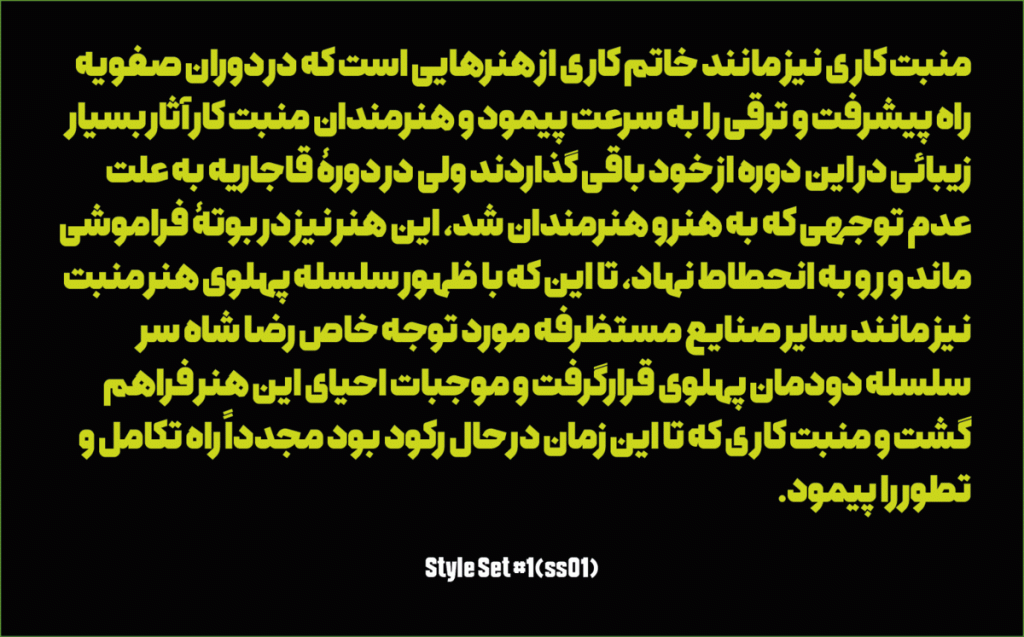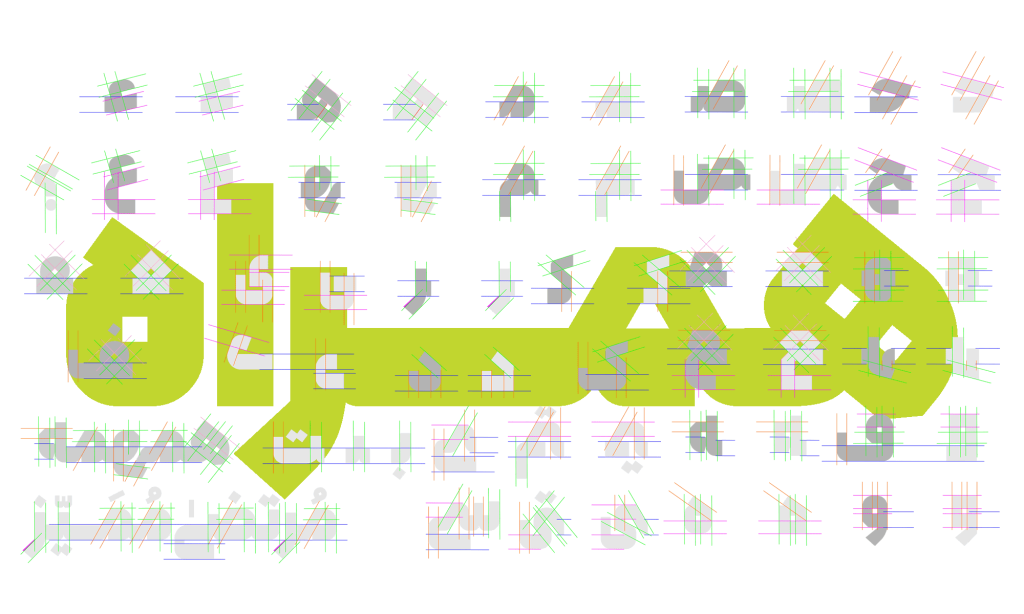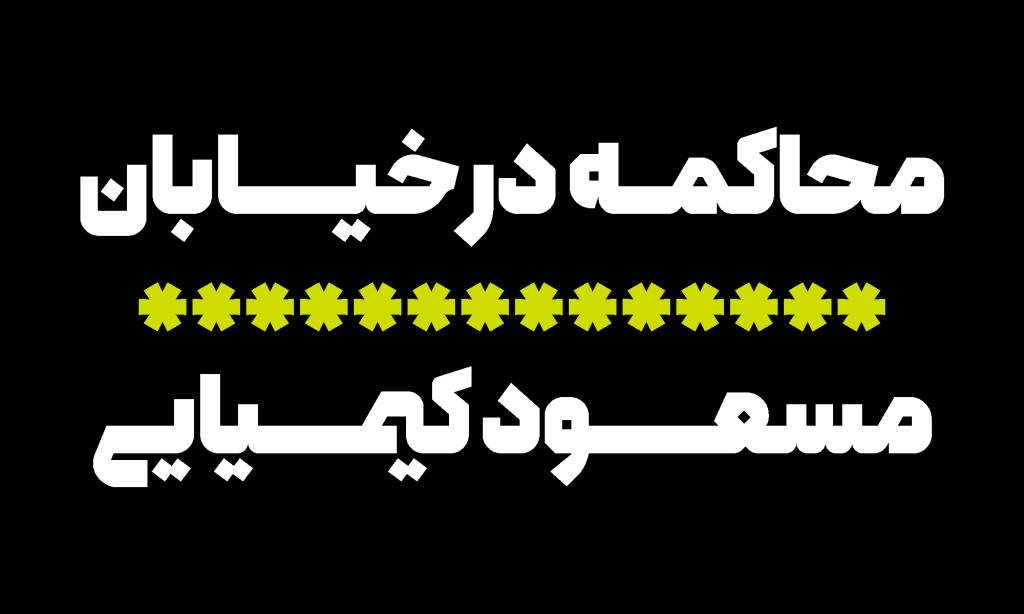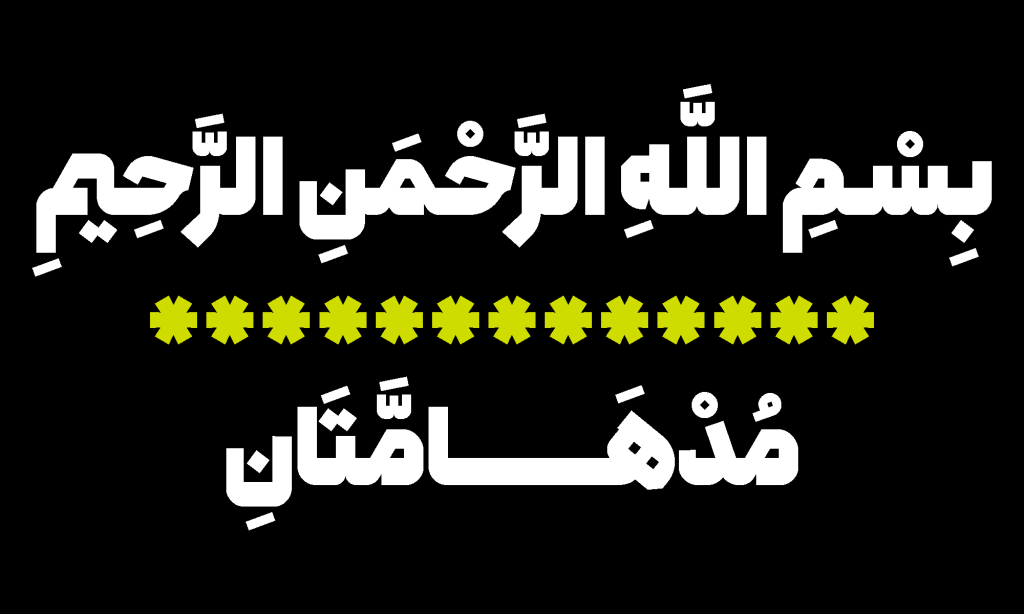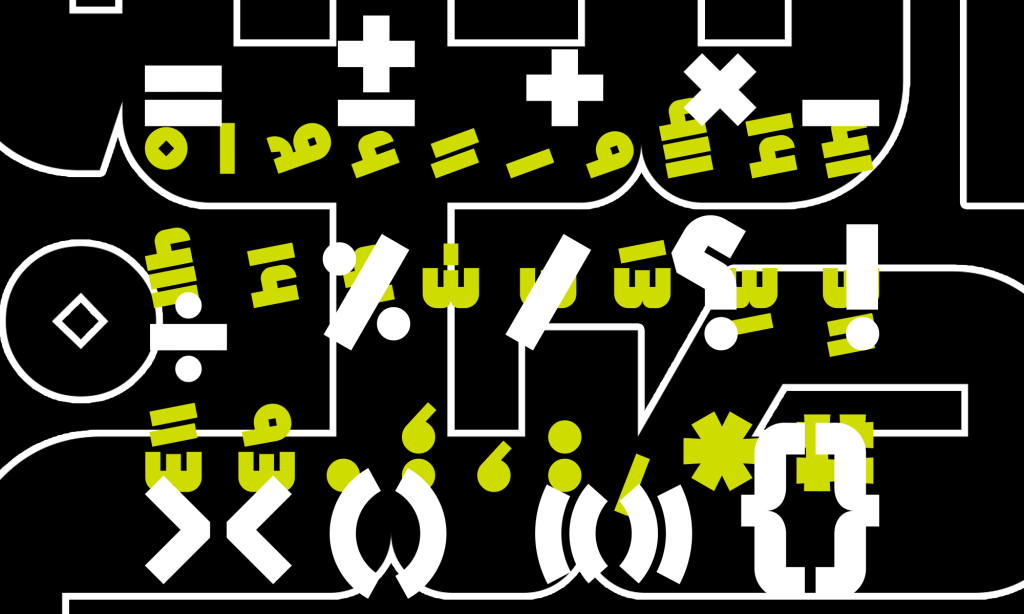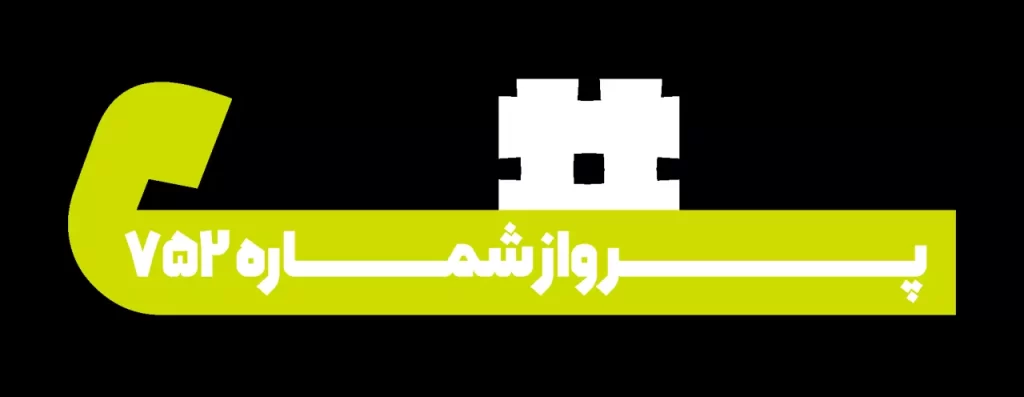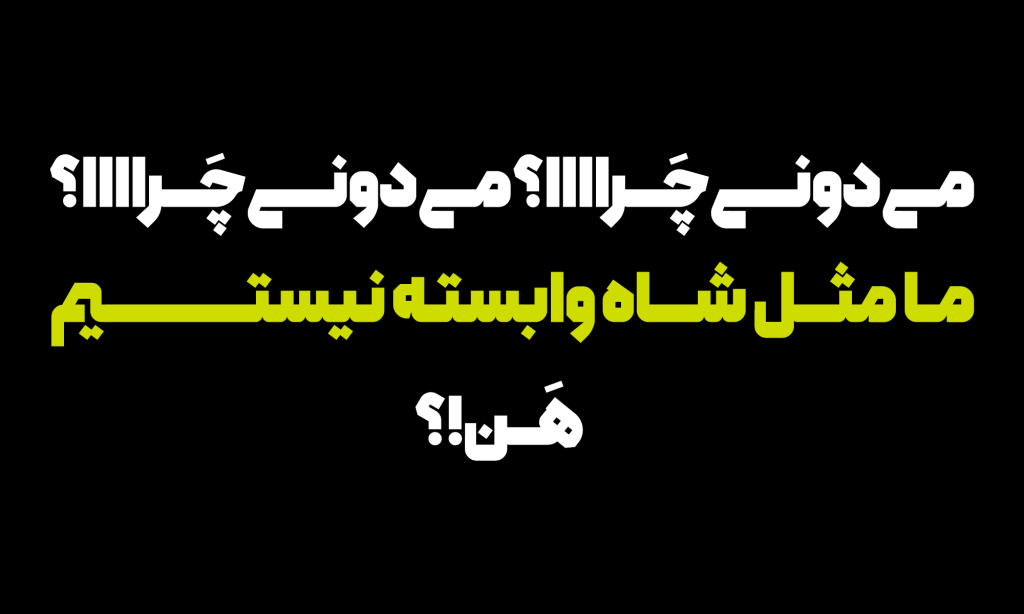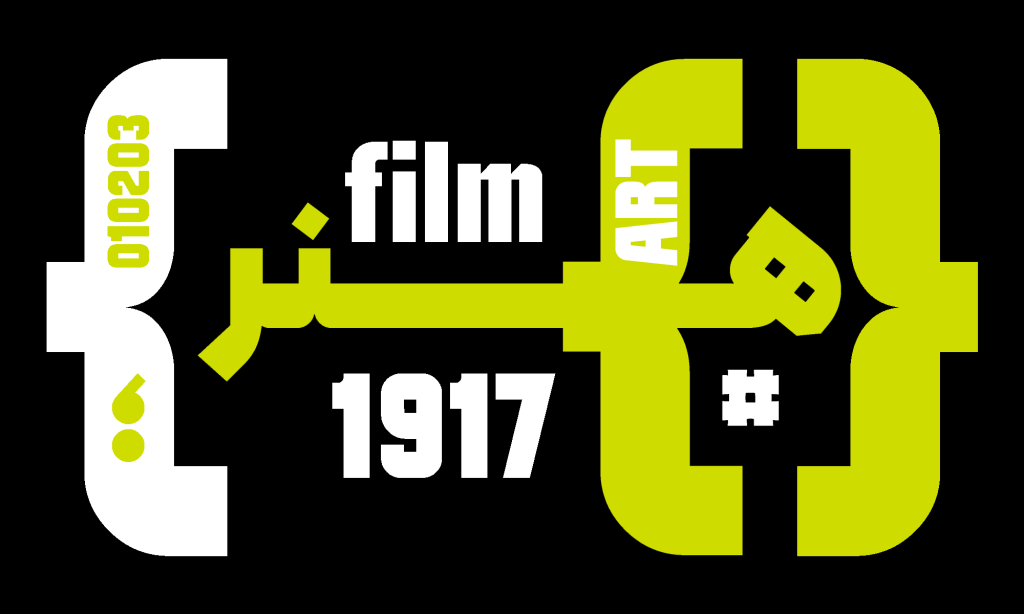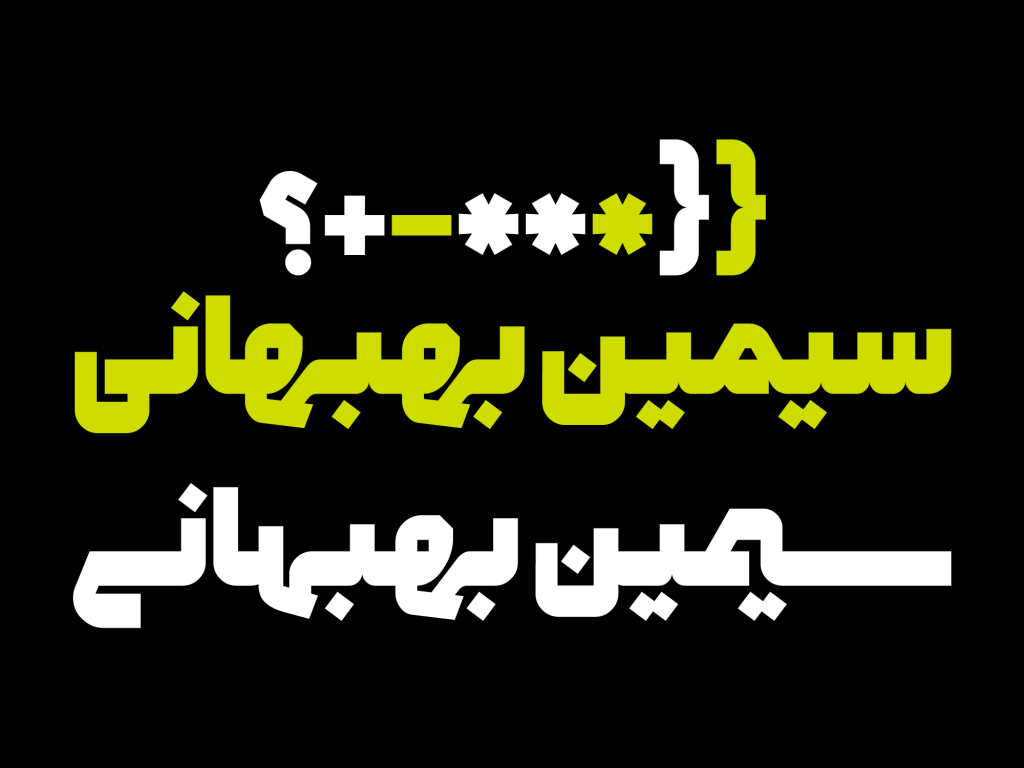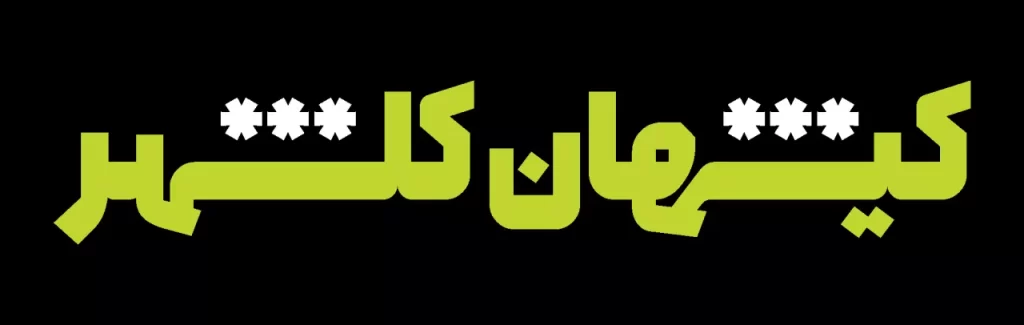
فونت همراه قلمی با ساختار بنایی و مستحکم
فونت همراه قلمی از خانواده هندسی از ساختار بنایی و متشکل از خطوط صاف و زوایای تند و تیز می باشد. فضای منفی داخل حروف و همچنین محیط کلی آن بسیار کم و حروف به خط کرسی نزدیک هستند که این سبب تاثیر گذاری و هماهنگی بیشتر در این تایپ فیس شده است.
همراه قلمی با شخصیتی به روز و نو
اگر کمی دقت در این قلم می توان دریافت که نقاط ضعف و قوت در این تایپ فیس بسیار نزدیک هم هستند. تمام حروف و لیگچرها به ساده ترین شکل ممکن طراحی شده اند و لیکن هریک دارای شخصیت نو و به روز می باشند. این تایپ فیس دارای یک وزن و مناسب استفاده در نوشتههای کوتاه است. این تایپ فیس توسط وحید یعقوبلو طراحی شده و توسط امین عابدی ساخته و توسعه داده شده است. وی همچنین فونت یکتا که تایپ فیسی نمایشی و تزئینی است را طراحی و ایجاد کرده است.
همراه شخصیتی بی باک و به روز دارد این قلم زیبا بی شک نگاه بینندگان را به خود جذب می نماید در زیر تصاویر مربوط به ایت تایپ فیس برای شما دوستان عزیز قرار داده شده است.